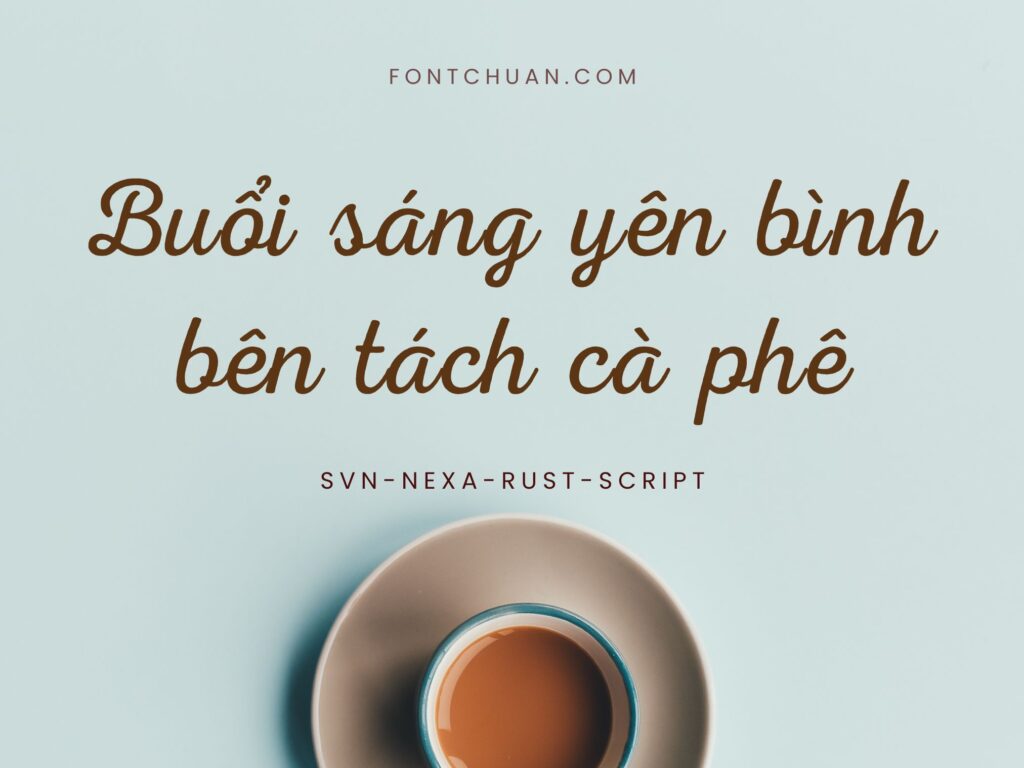
Font SVN Nexa Rust Script Việt Hóa
Tác giả Font: Radomir Tinkov, Svetoslav Simov
Font SVN Nexa Rust Script là phiên bản Việt hóa của kiểu chữ Nexa Rust Script, được thực hiện bởi STYLEno.1 Fonts. Nexa Rust Script là một phần của hệ thống font đa dạng Nexa Rust, được thiết kế bởi Radomir Tinkov, Svetoslav Simov, Ani Petrova và Vasil Stanev từ Fontfabric. Hệ thống này bao gồm các phân họ: Sans, Slab, Script, Handmade và Extras, mỗi phân họ mang đến một phong cách riêng biệt với vẻ ngoài thô ráp và ấm áp. Nexa Rust Script nổi bật với các nét chữ viết tay mềm mại, tự nhiên, tạo cảm giác thân thiện và gần gũi. Font này bao gồm đầy đủ các ký tự chữ hoa, chữ thường, chữ số và dấu câu, hỗ trợ đa ngôn ngữ. Font này phù hợp cho nhiều mục đích sử dụng khác nhau như thiết kế logo, tiêu đề, bao bì sản phẩm và các ấn phẩm truyền thông.
SVN Nexa Rust Script lý tưởng cho các dự án thiết kế yêu cầu sự tự nhiên và thân thiện, như thiết kế logo, tiêu đề, bao bì sản phẩm và các ấn phẩm truyền thông. Các ngành nghề như quảng cáo, giáo dục và ẩm thực có thể tận dụng font này để tạo điểm nhấn trong thiết kế. Ngoài ra, font cũng thích hợp cho các sự kiện như Tết, Giáng sinh, Valentine và các lễ hội khác.